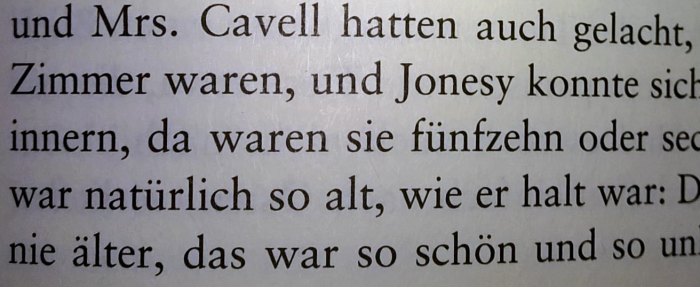
Es sieht Times New Roman ähnlich, aber da geht das "J"  z.B. nicht so weit nach unten.
Das Foto stammt aus dem Buch "Duddits" von Stephen King. Es kam 2001 im Ullstein Verlag.post-34824-0-27991400-1462421087_thumb.p
Typeface: Bembo
Designer: Stanley Morison and Monotype Staff
Year:  1929, 1990
Publishers: Adobe and Monotype
Alternates: Bergamo SM, Cardo, Aldine 401
Influence on: JY Aetna
Based on the original designs of Francesco Griffo,
who cut the type used in 1495 by Aldus Manutius to
print Cardinal Bembo's tract, 'De Aetna'.
An OpenType font that includes both lining and
oldstyle figures.
* Cardo ist eine freie Version der Bembo (SIL-OFL)
* Aldine 401 ist die Bitstreamversion die mit Corel-Produkten wie Draw mitgeliefert wird.
* Bergamo ist der Name der kommerziellen Version von Softmaker und/oder Fontsite
hm, die Bembo kommt schon nahe dran, die ist es aber nicht. f, c sind deutlich anders …
Wenn du dich nur auf die Garamond beziehst: Ullstein verwendet aktuell meist die "Garamond Premier Pro" von Adobe, nicht die "Adobe Garamond".
Die Schrift hat's mir irgendwie angetan :)
Ist meiner unerheblichen Meinung nach auch die schönste der Garamönder ;-)
Bei "a" und "s" hätte ich eher die Sabon vermutet; in einem Druck von 2001 wäre doch etwas von der Kantigkeit des Stempel-Garamond-"a" erhalten geblieben, oder? Ich habe allerdings nicht alle Buchstaben im Detail verglichen. Gibt's in dem Buch 'ne kursive Passage?
Oh ja, wie recht du hast. Auch das untere Ende des "J" und des "y" sehen bei der Sabon Schrift dem Foto ähnlicher.